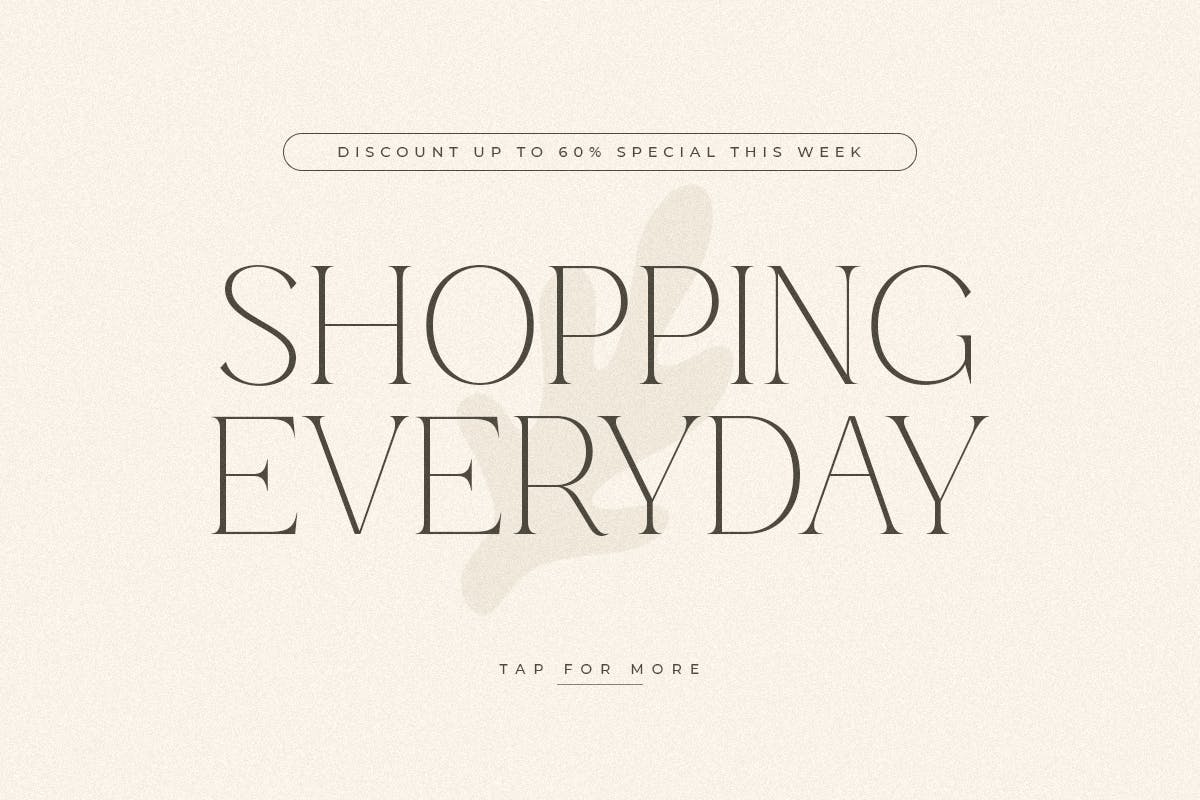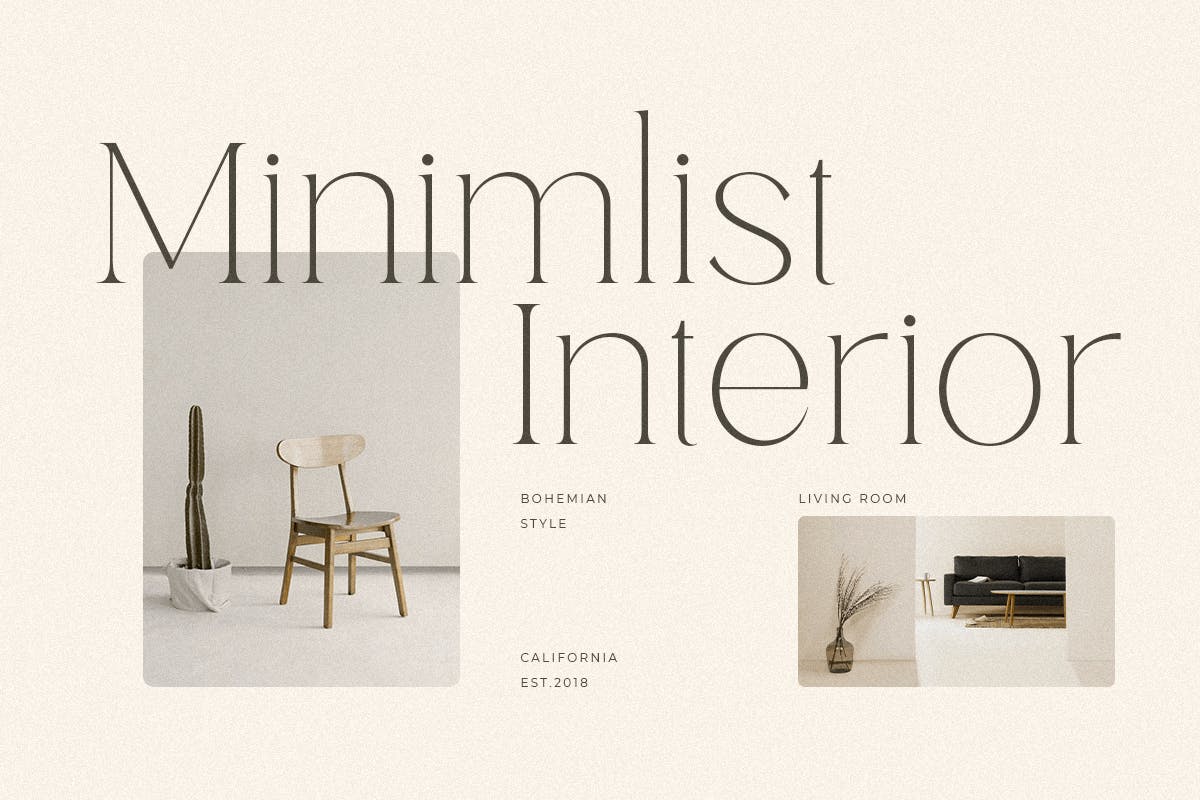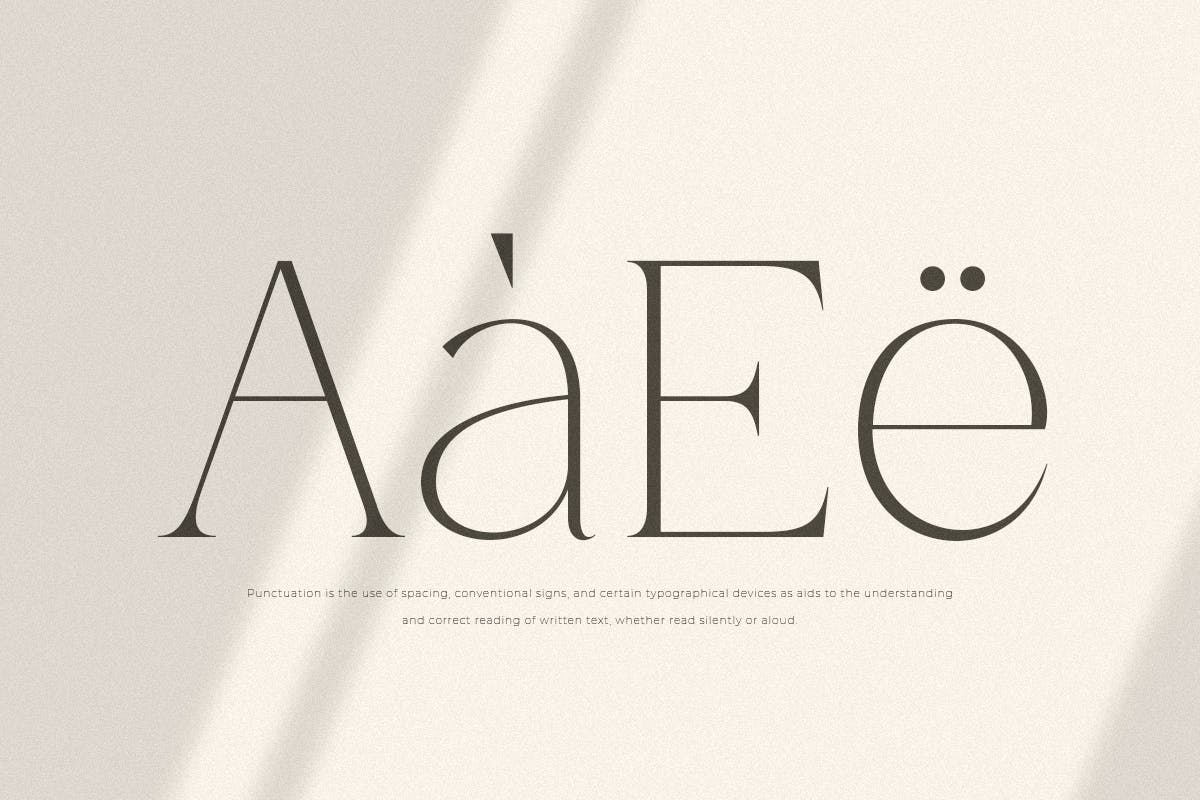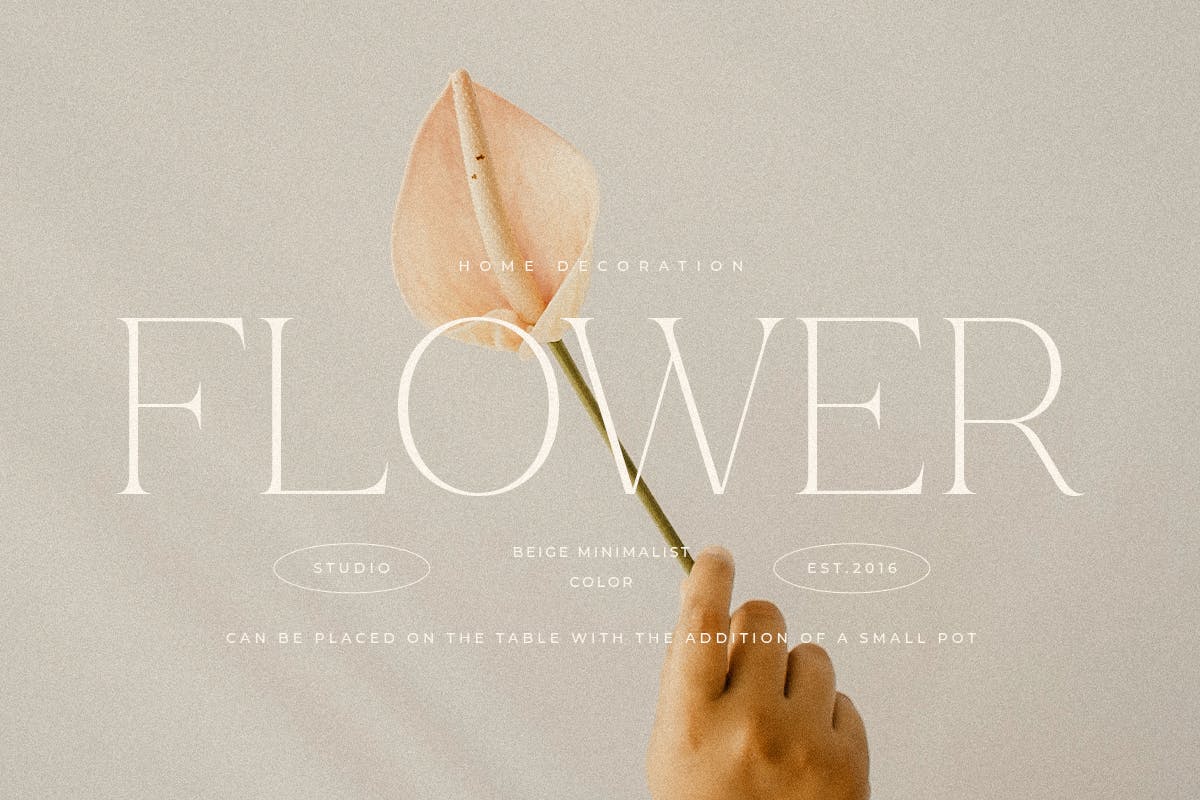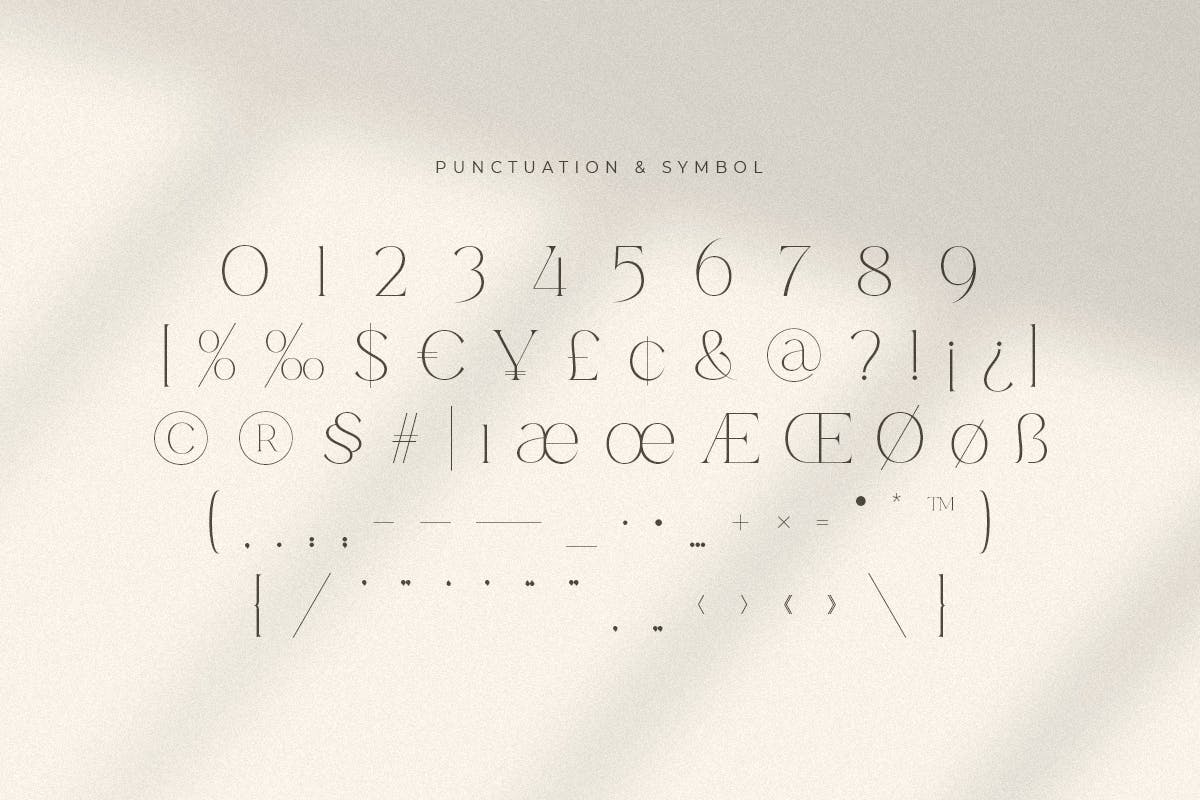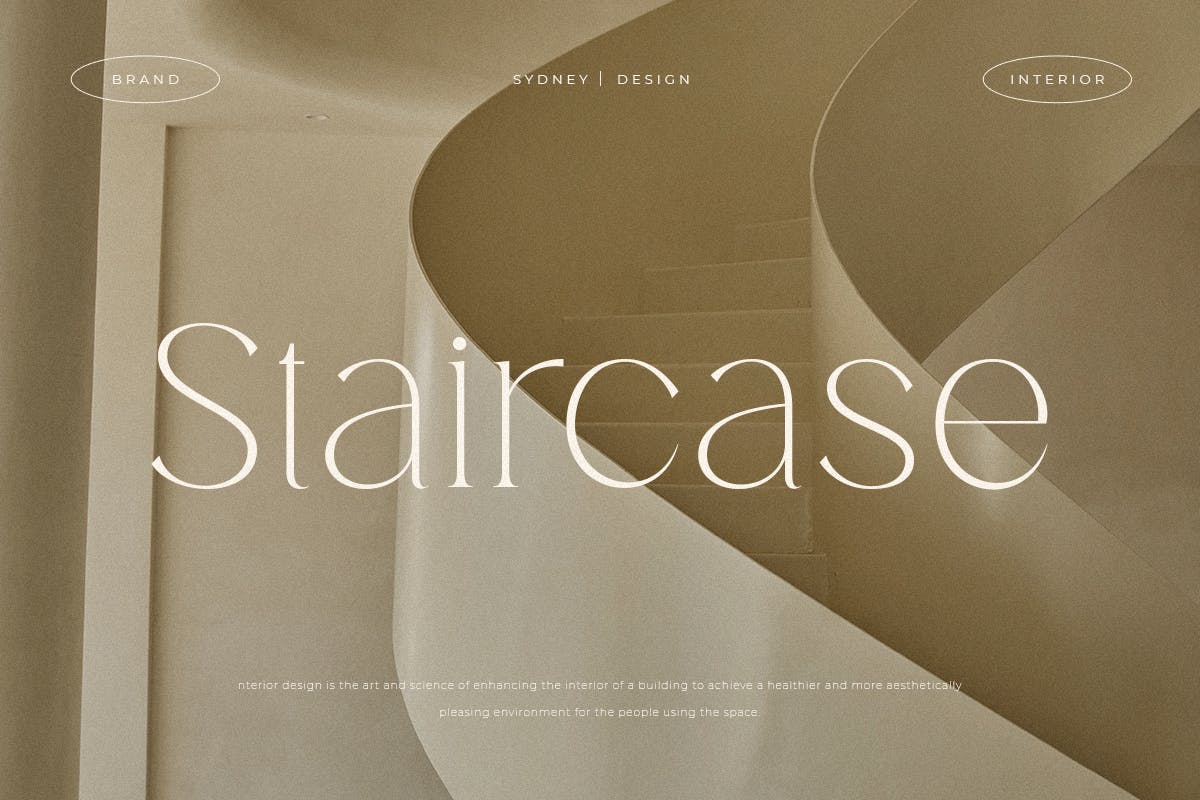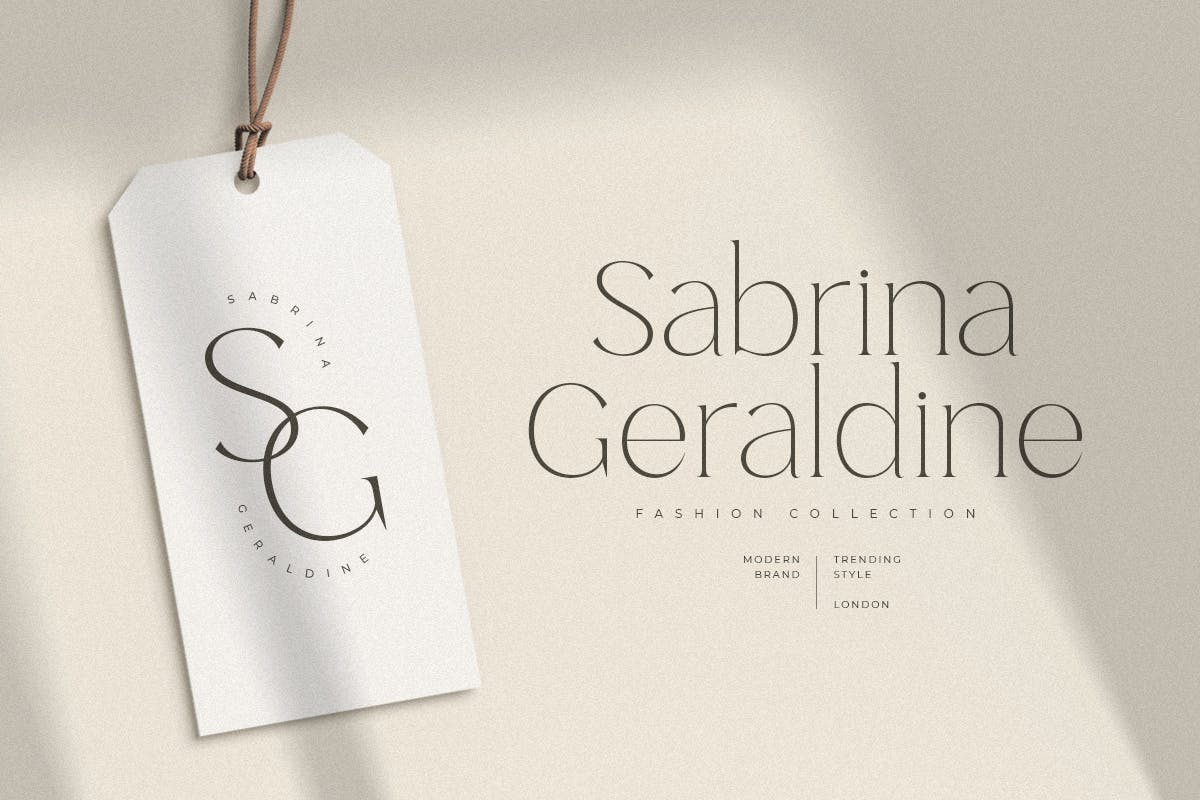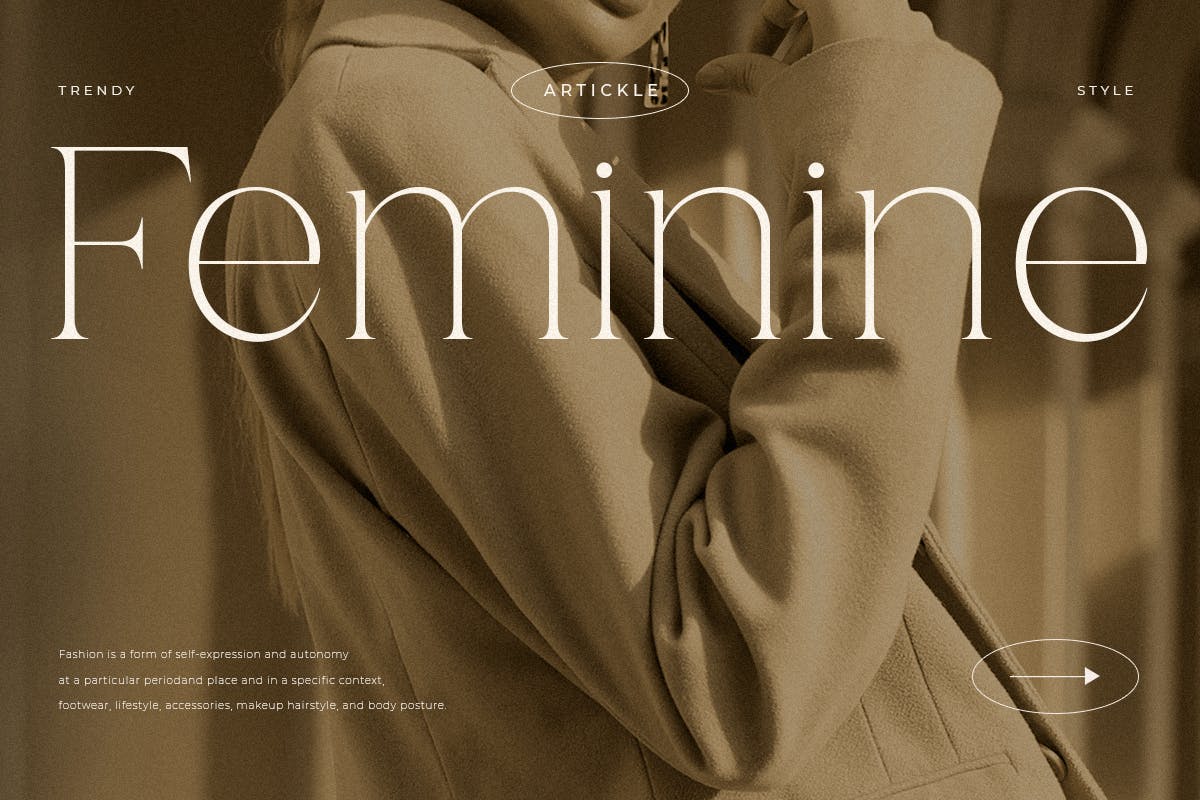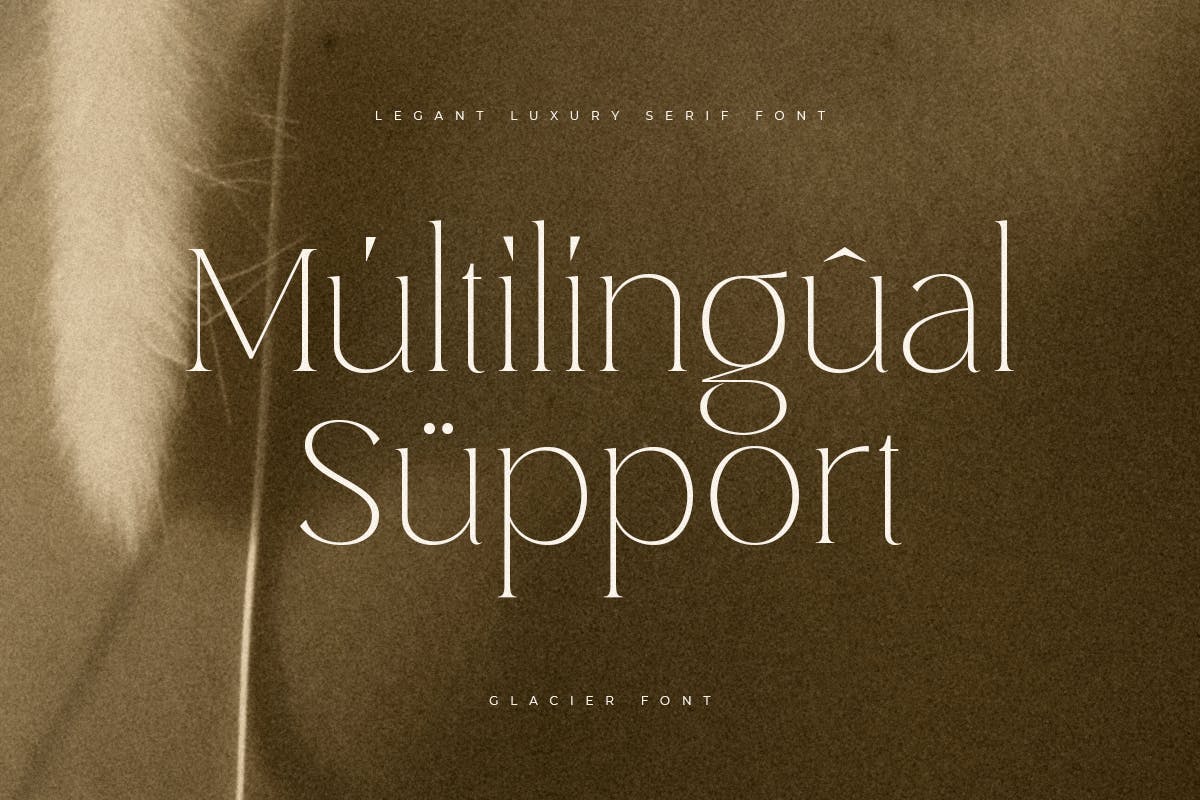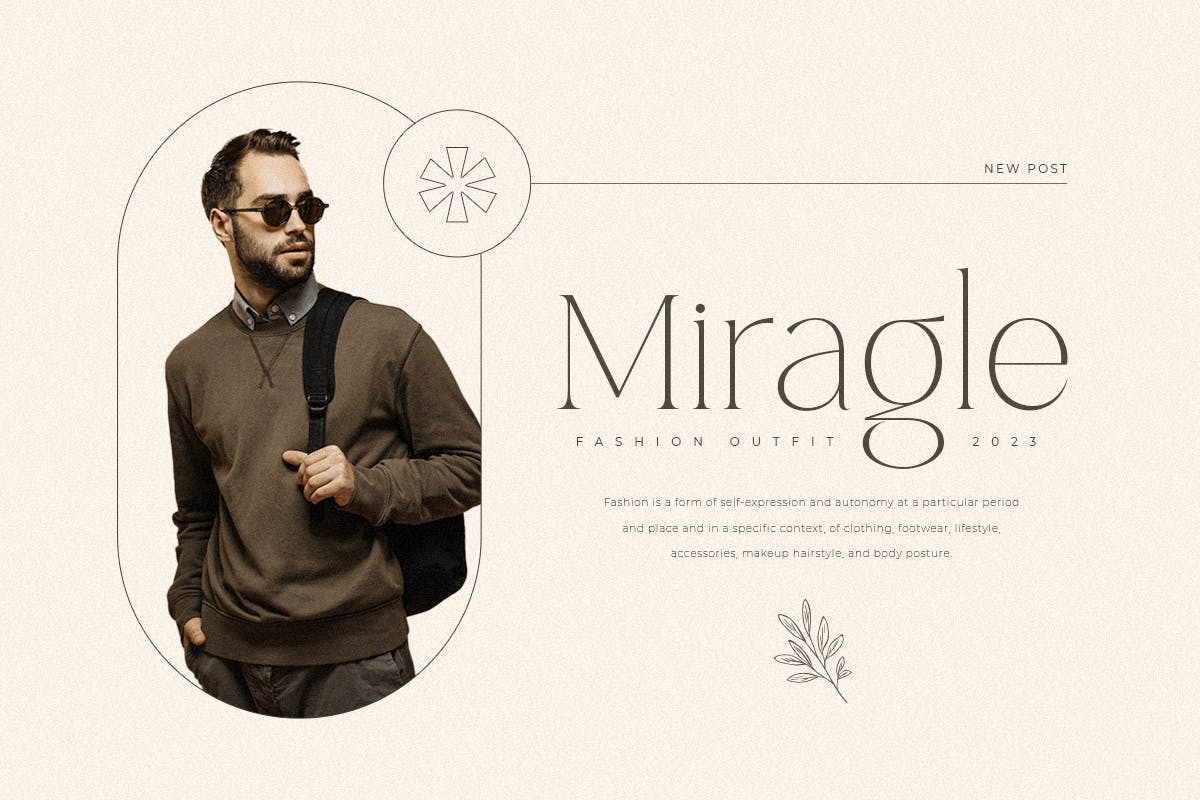
فونت Glacier یک فونت مدرن، شیک و لوکس است که بهطور ویژه برای نیازهای برندینگ مجلل طراحی شده است. با شکل منحصر به فرد خود، این فونت به ارزش برند شما افزوده و طراحیهای شما را بسیار زیباتر و مدرنتر میکند. این فونت بهطور خاص برای طراحان و مالکان محصولات که به دنبال راهحلهایی برای زیباتر کردن طراحیهای خود هستند، مناسب میباشد. همچنین، ما شخصیتهای مختلفی را برای فونت Serenity آماده کردهایم تا به شما کمک کنیم تا بینهایت تنوع برای نیازهای خلاقانه خود ایجاد کنید.